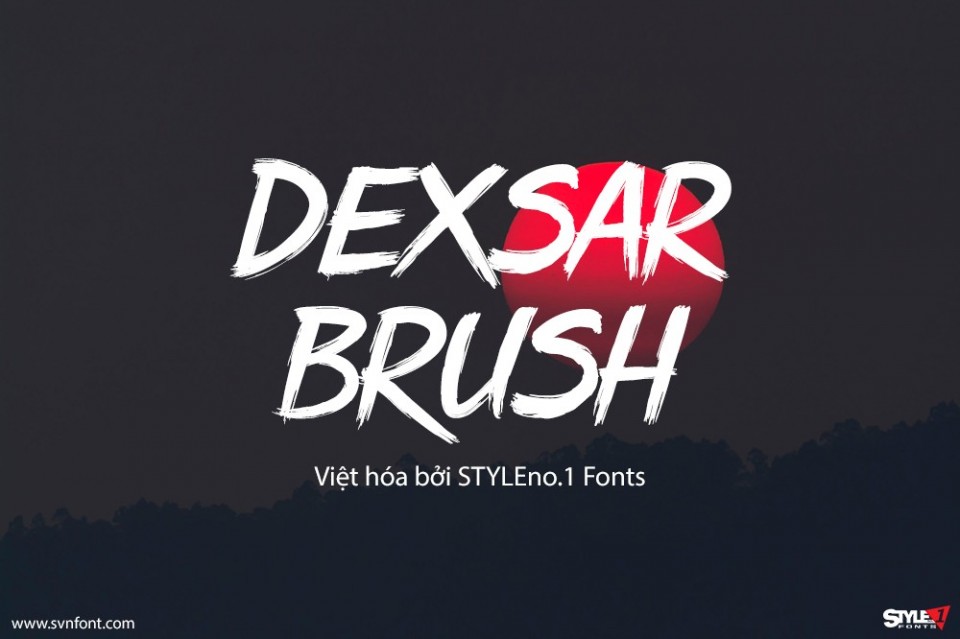
Font việt hóa SVN Dexsar Brush
Giới thiệu về Font việt hóa SVN Dexsar Brush
Trong thế giới sáng tạo, việc lựa chọn một Font Miễn Phí chất lượng luôn là ưu tiên hàng đầu của các bạn học sinh và giáo viên. Font việt hóa SVN Dexsar Brush là một bộ font chữ mang phong cách brush đầy cá tính, mô phỏng những nét cọ vẽ thủ công mạnh mẽ và phóng khoáng. Với sự tỉ mỉ trong khâu việt hóa, bộ font này giúp người dùng dễ dàng truyền tải thông điệp một cách ấn tượng mà không lo lỗi font khi gõ tiếng Việt có dấu.
Đặc điểm nổi bật của Font việt hóa SVN Dexsar Brush
Phong cách nghệ thuật phóng khoáng
Đúng như tên gọi, Font việt hóa SVN Dexsar Brush sở hữu những đường nét thô mộc, tự nhiên như được vẽ bằng cọ sơn thật. Sự kết hợp giữa các nét thanh và nét đậm tạo nên một nhịp điệu hình ảnh sống động, rất phù hợp cho các chủ đề về thể thao, âm nhạc hoặc các sự kiện trường học năng động. Font chữ này mang lại cảm giác gần gũi nhưng không kém phần chuyên nghiệp cho các sản phẩm đồ họa.
Khả năng ứng dụng đa dạng
Nhờ vào bộ ký tự đầy đủ và hỗ trợ tốt tiếng Việt, bạn có thể sử dụng font này cho nhiều mục đích khác nhau. Từ việc thiết kế bìa báo tường, làm tiêu đề cho các slide thuyết trình sinh động đến tạo poster quảng bá sự kiện ngoại khóa, SVN Dexsar Brush đều đáp ứng hoàn hảo. Đây là công cụ đắc lực giúp bài làm của học sinh trở nên nổi bật và thu hút ánh nhìn từ ban giám khảo cũng như thầy cô.
Hướng dẫn sử dụng hiệu quả
Để tận dụng tối đa vẻ đẹp của Font việt hóa SVN Dexsar Brush, bạn nên kết hợp nó với các màu sắc rực rỡ hoặc nền có kết cấu giấy vẽ. Tránh dùng font cho các đoạn văn bản dài vì đặc tính brush có thể gây khó đọc; thay vào đó, hãy dùng cho các từ khóa chính. Hy vọng bạn sẽ có những trải nghiệm tuyệt vời cùng Font Miễn Phí, Font Việt Hóa, Font việt hóa SVN Dexsar Brush trong các dự án học tập sắp tới của mình.